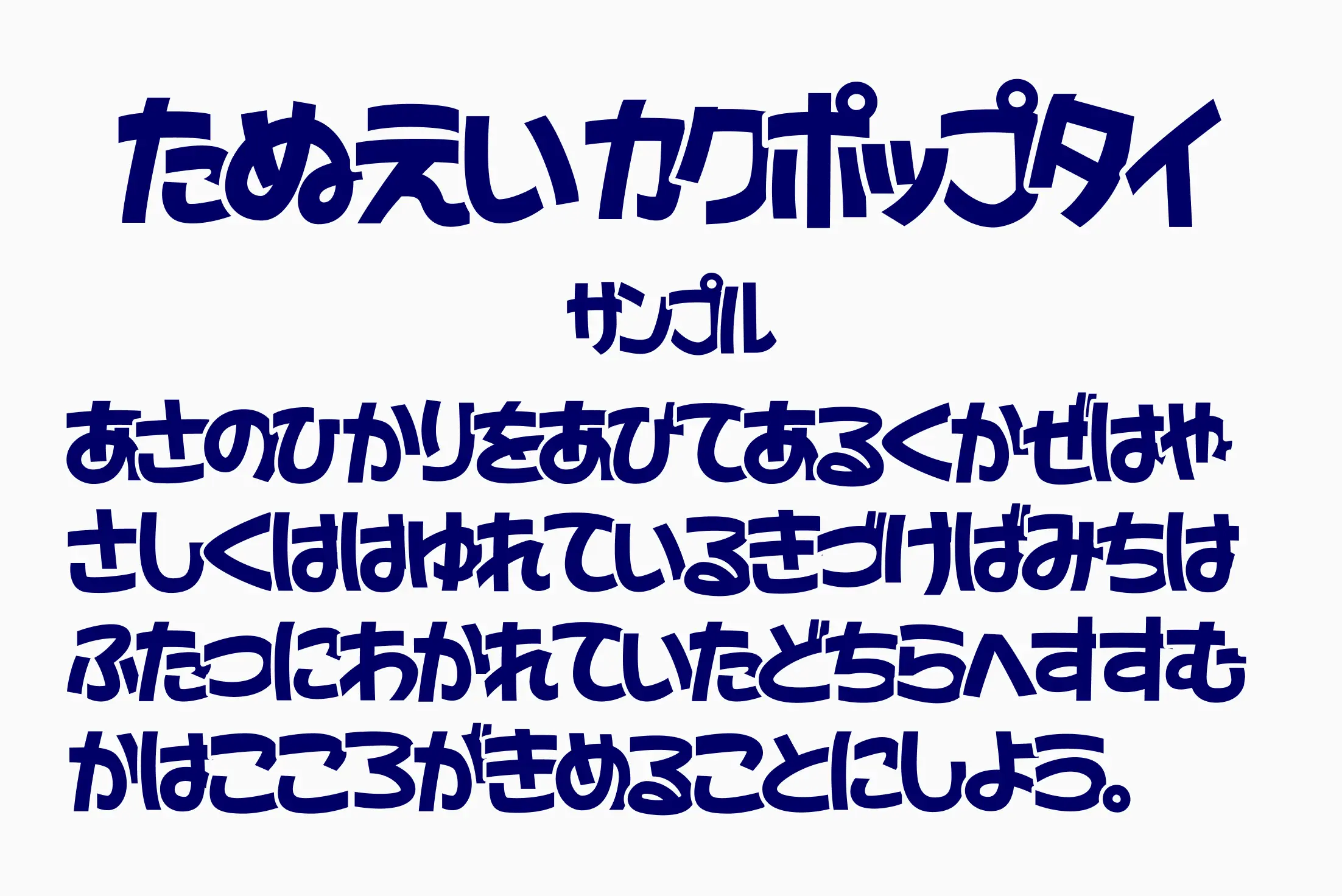
やわらかな丸みと元気な角ばりが特徴のポップなフォント。ひらがな・カタカナ・アルファベット・数字にゆるっと力強い存在感が特徴の、たぬきフォントシリーズの角ポップ体。どこか抜け感のあるフォルムで、楽しげなデザインや親しみやすい場面にぴったりです。手描き風の個性を活かした見出しやロゴ制作にもおすすめ。
たぬえいカクポップタイ